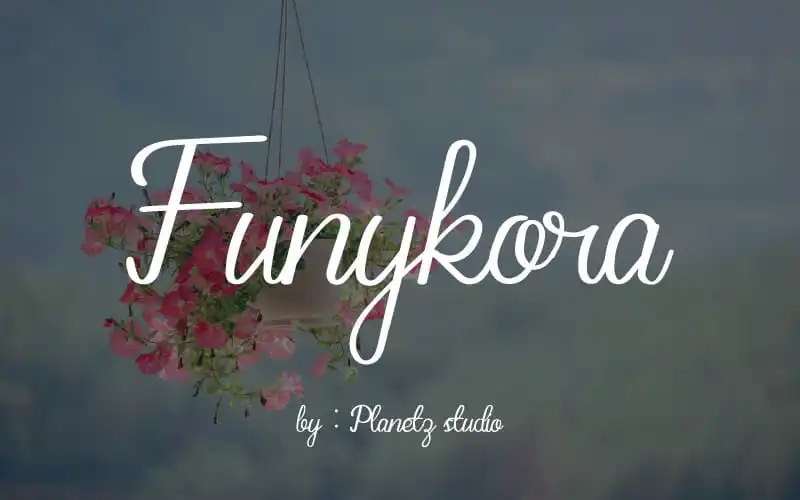
Funykora Handwritten Font – Download Grátis
A ‘Funykora Handwritten Font’ é uma delicada e afetuosa fonte escrita a mão que se destaca pela sua personalidade relaxada e acessível. Esse tipo vem para todos os ambientes de design, desde identidades corporativas e cartões de visita até cartas de casamento e posts nas redes sociais, promovendo um toque delicado e amigável a qualquer projeto. Como sugere o nome do designer planetz studio, esta fonte é uma escolha perfeita para criar gráficos de arte luminoso para cartazes, como cartões de aniversário infantis e postais românticos. Com um toque suave e encantador, a ‘Funykora Handwritten Font’ torna-se o ideal companheiro para estilos criativos e leves, oferecendo uma versatilidade que se adapta a diversos usos.